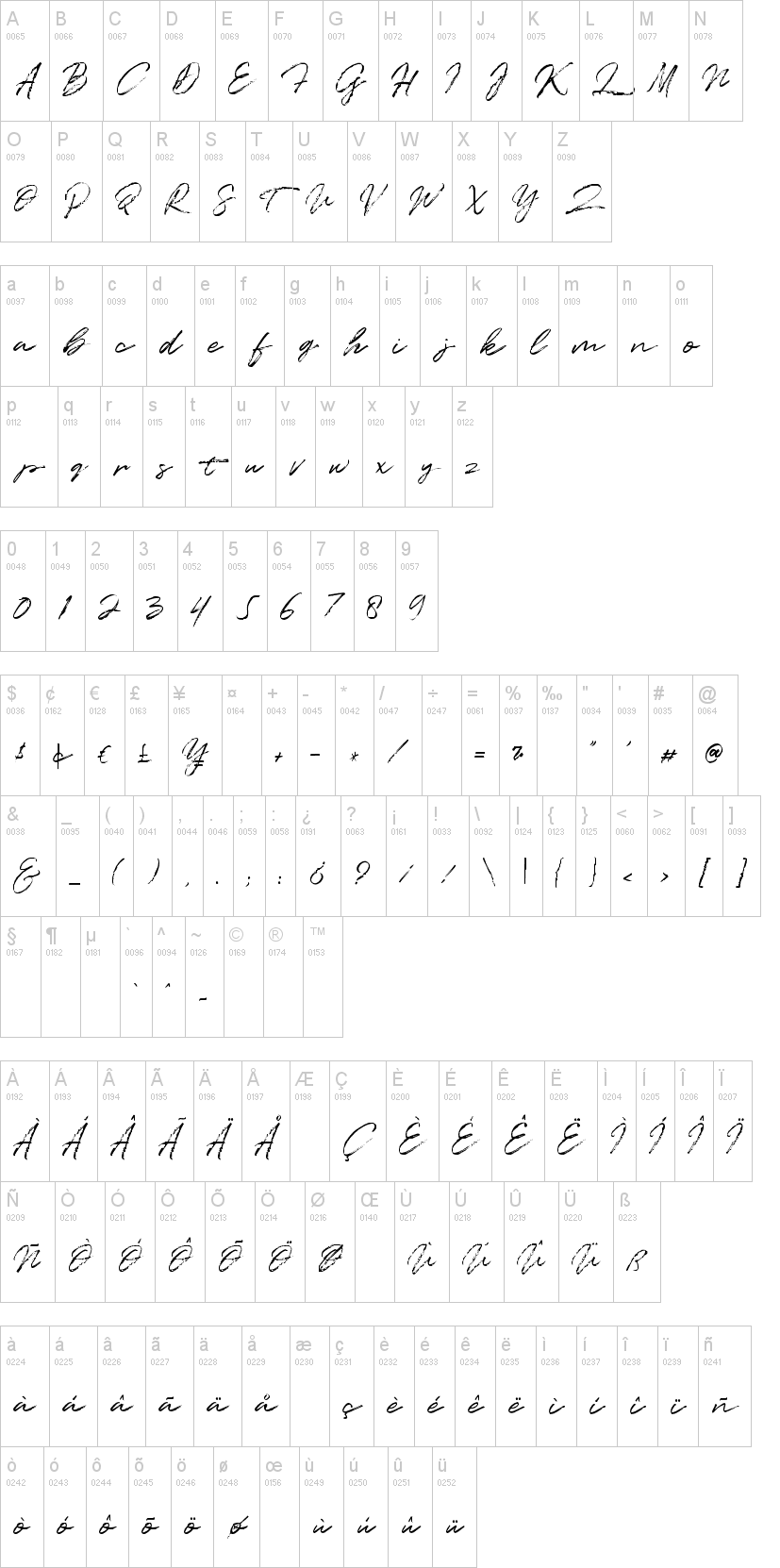
Quentin 是一款基于罗马文字的细长字体,由英国设计师Tom Kennedy设计,该字体以精致的细长字体设计而闻名,具有古典的外观,而且可以与其他字体非常融洽地搭配。Quentin 字体的字形曲线精致,细节处理精细,它的字形设计比较简约,具有清晰的视觉效果,可以帮助用户更好地表达消息。Quentin 字体适用于多种文字设计,可以用于书籍、杂志、标志、海报、海报等。内容介绍
Quentin是一款非常不错的手写艺术字体,具有很好的视觉感,适合于文化类的宣传设计、商业类品牌的广告和产品包装设计以及个性化文字排版等较多场景。